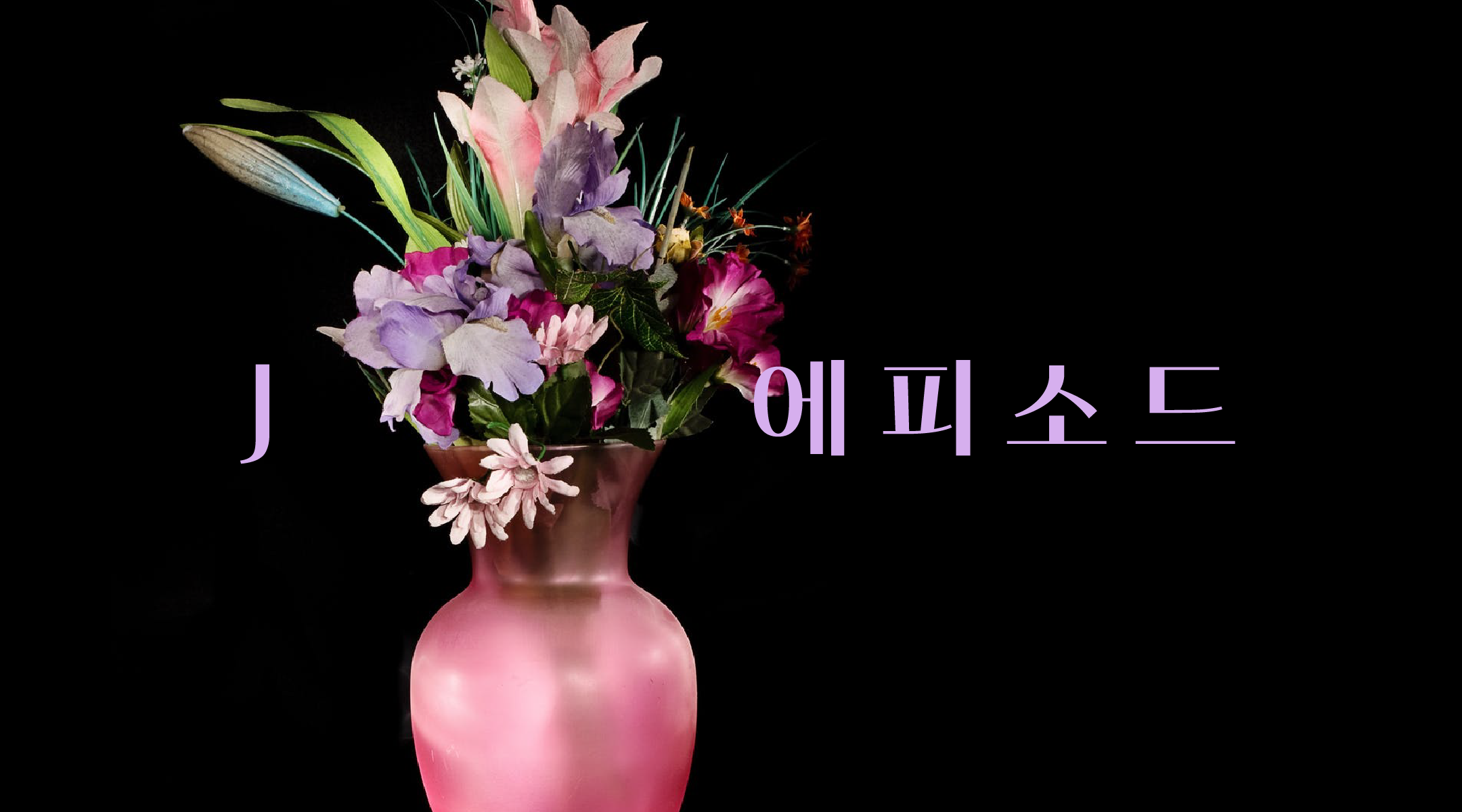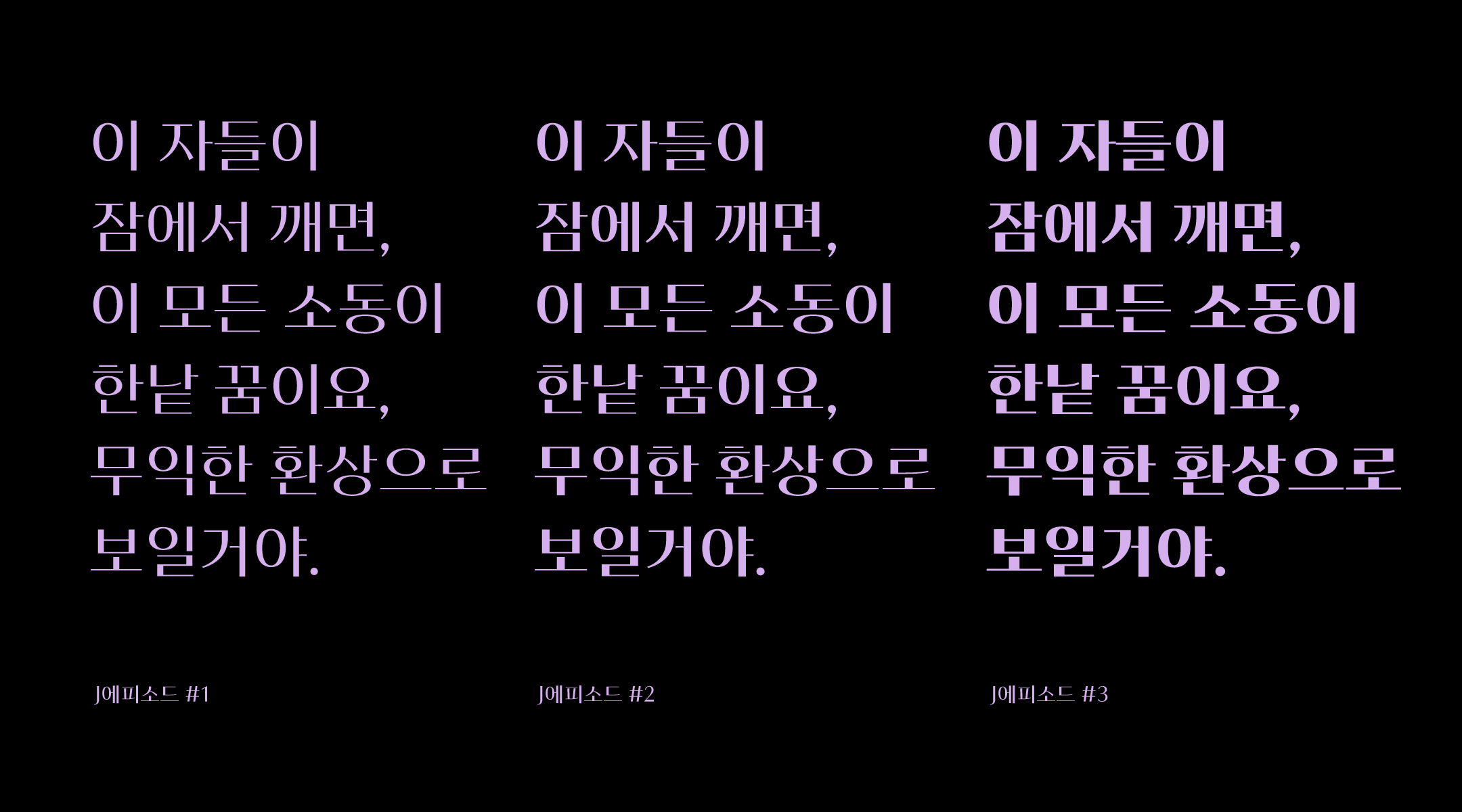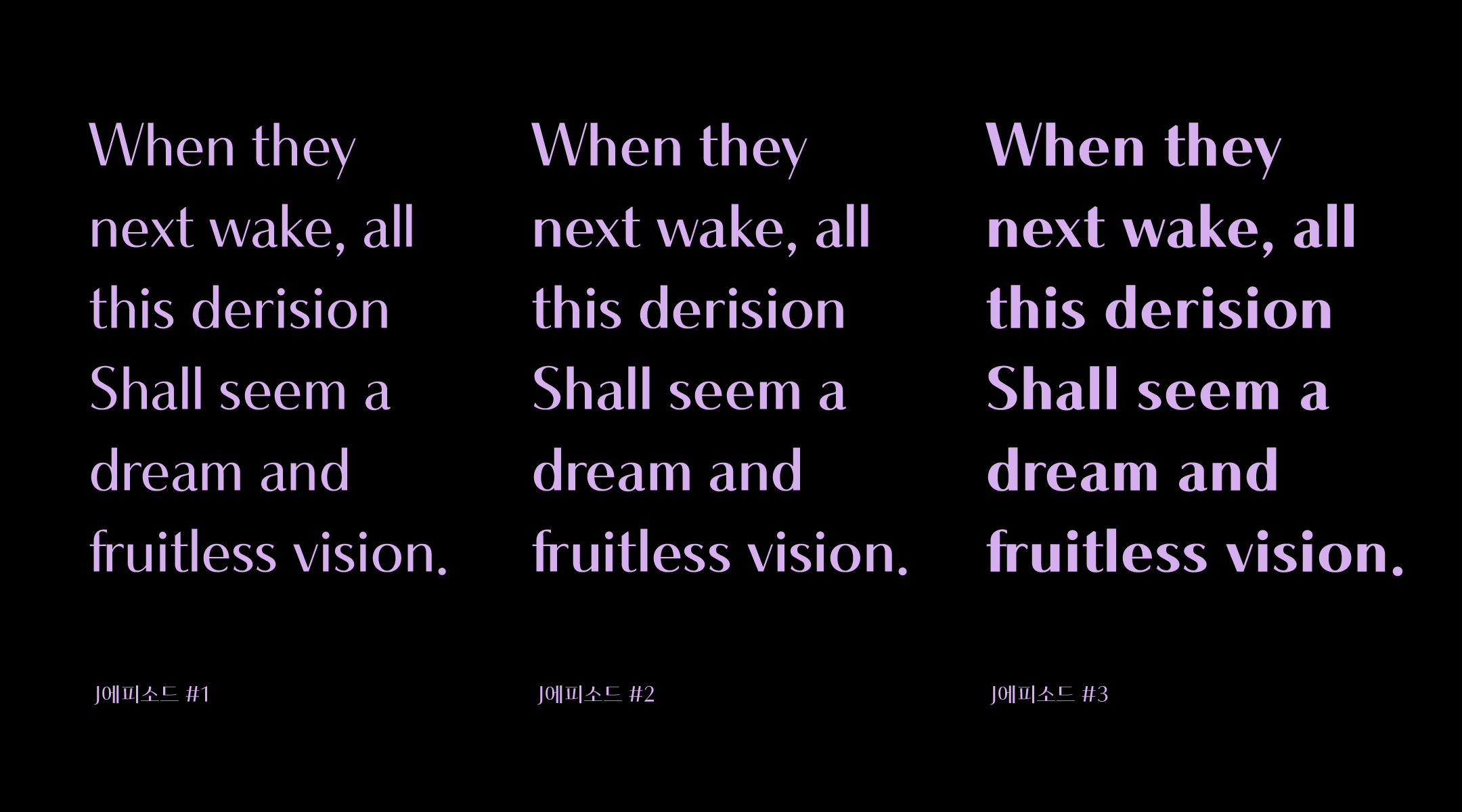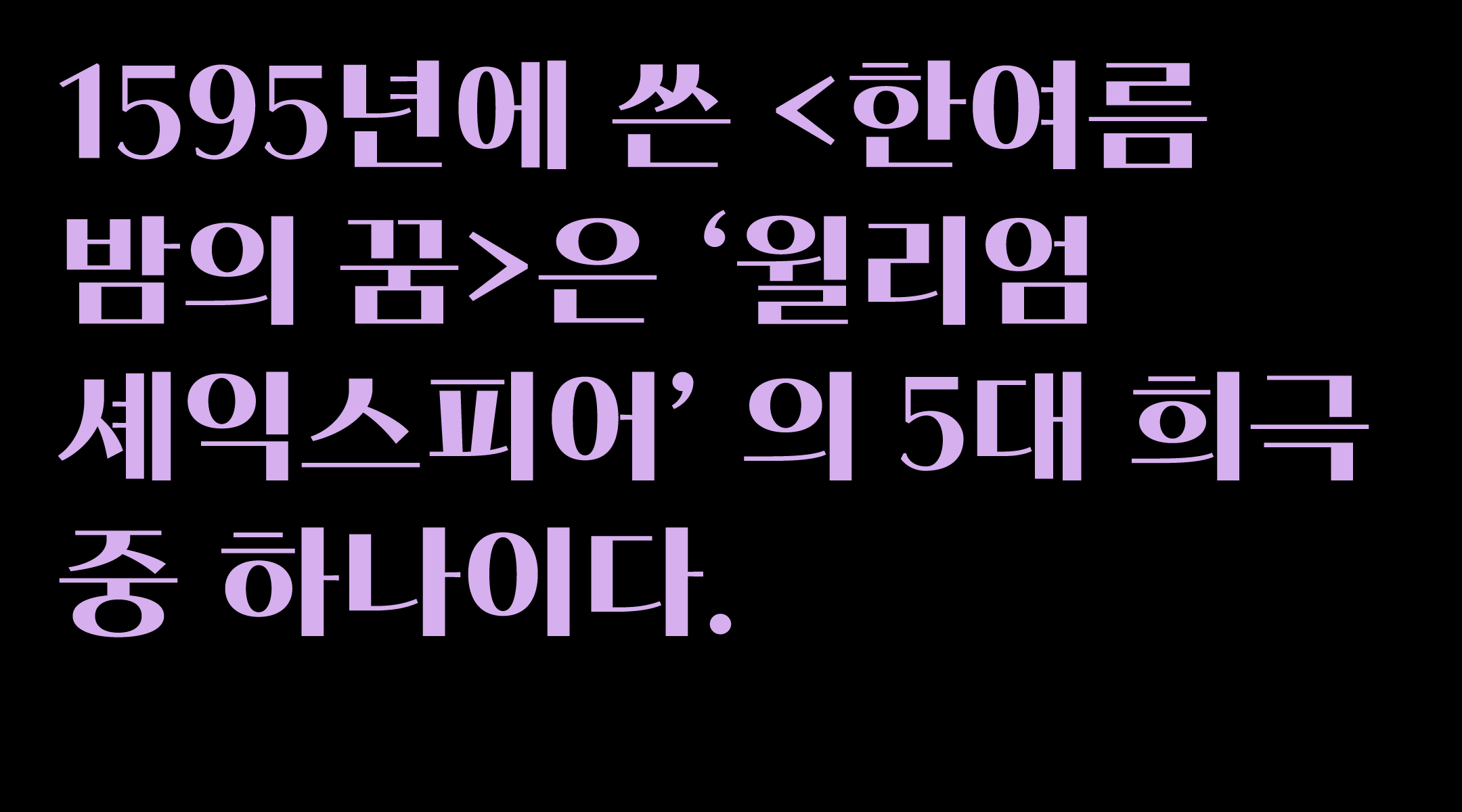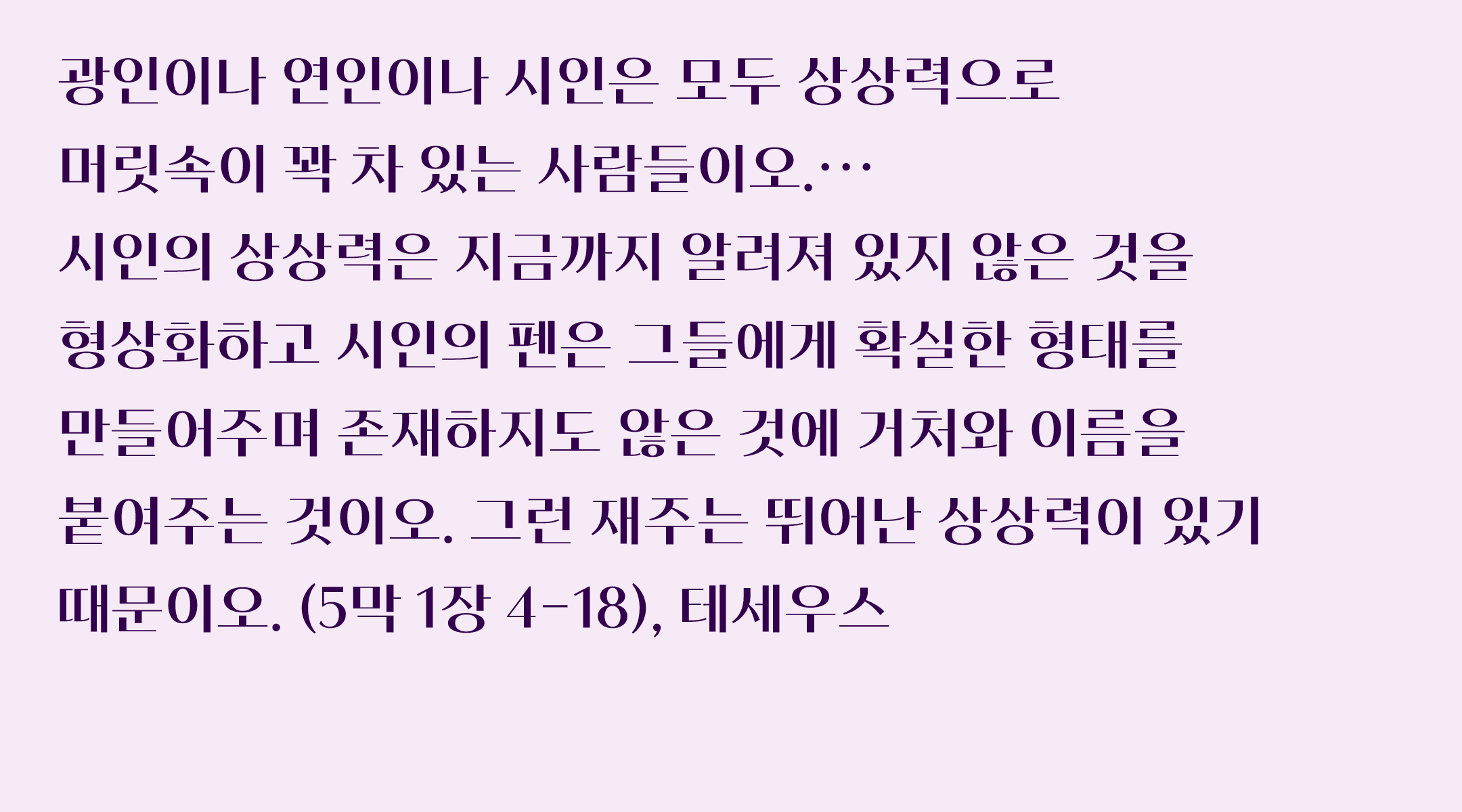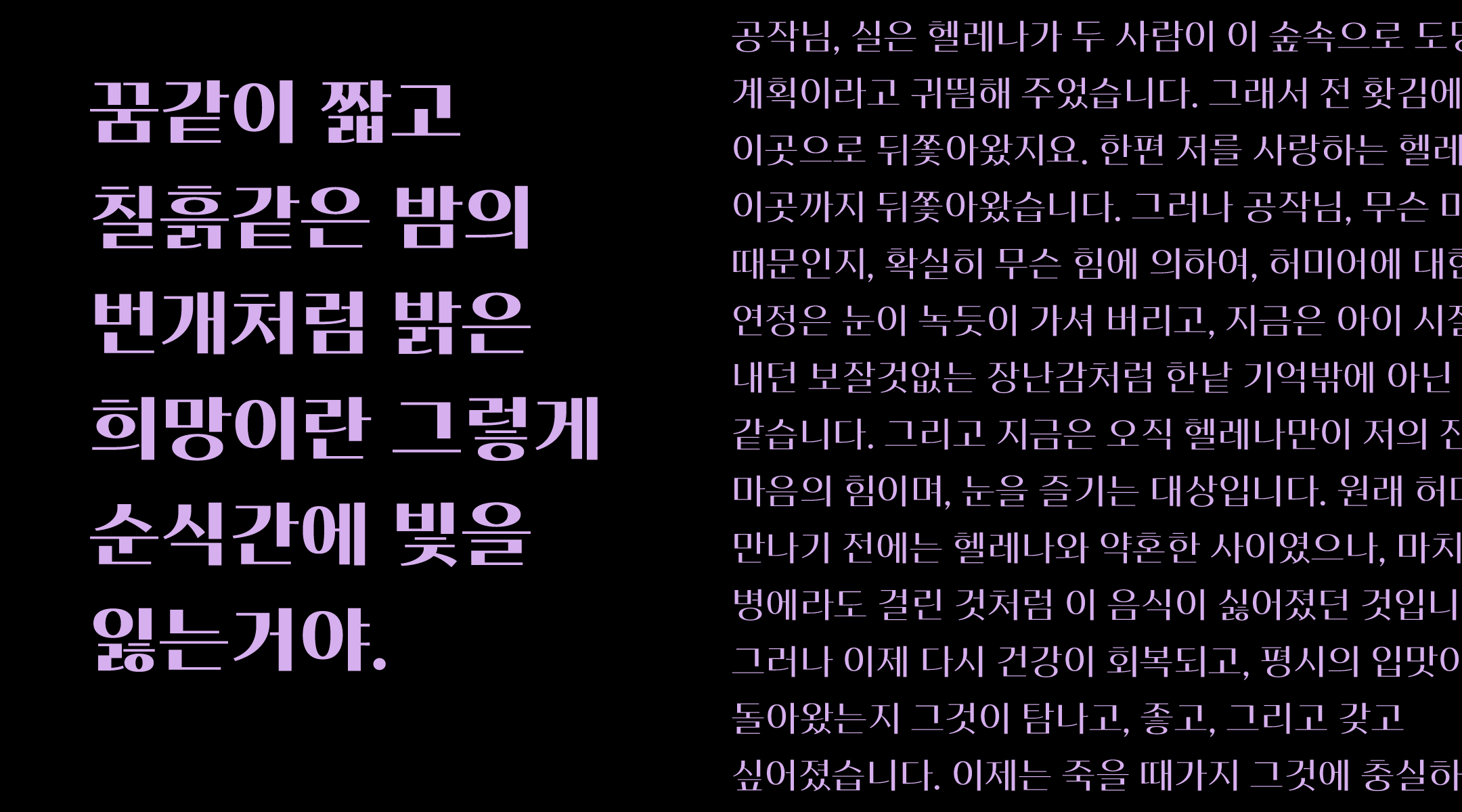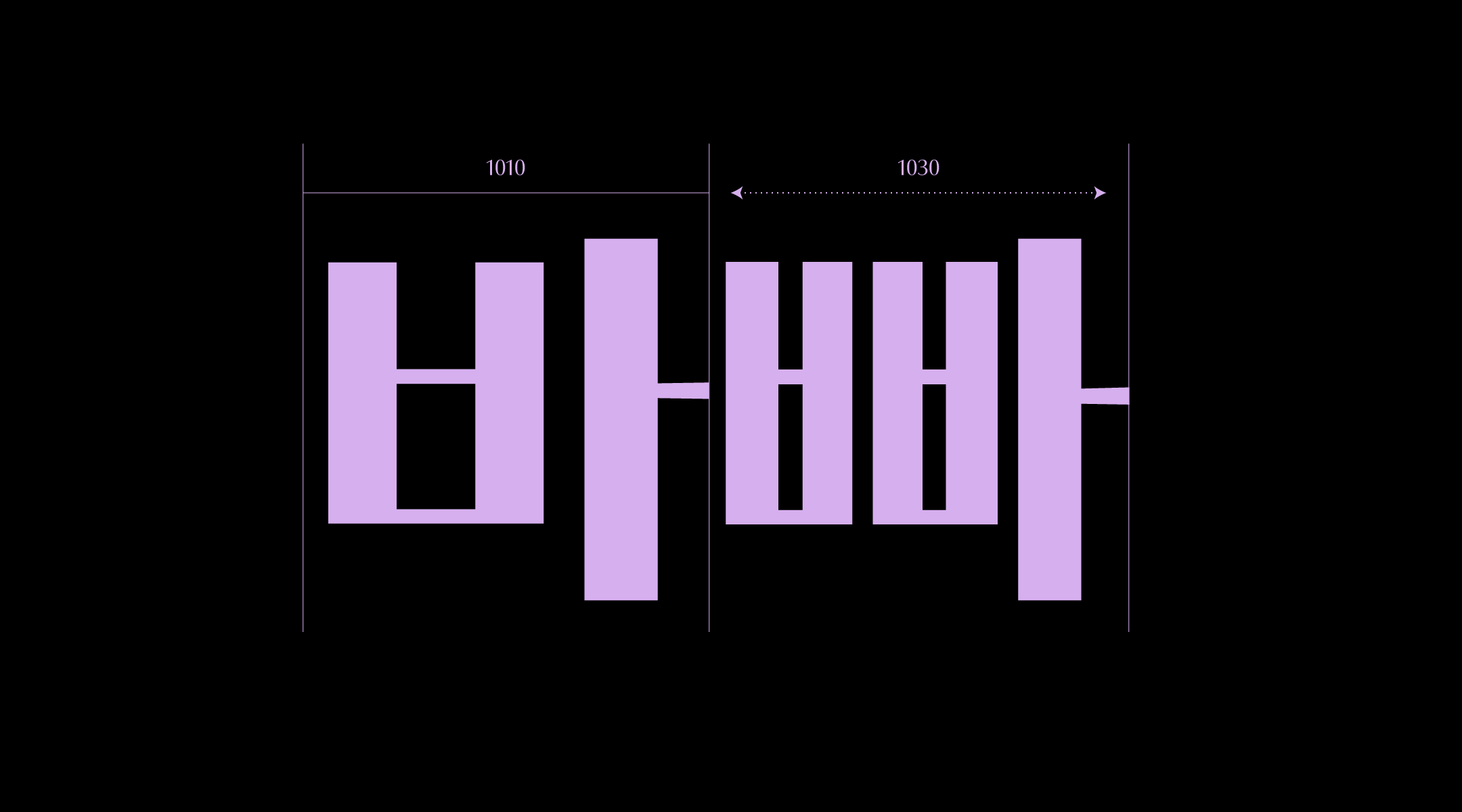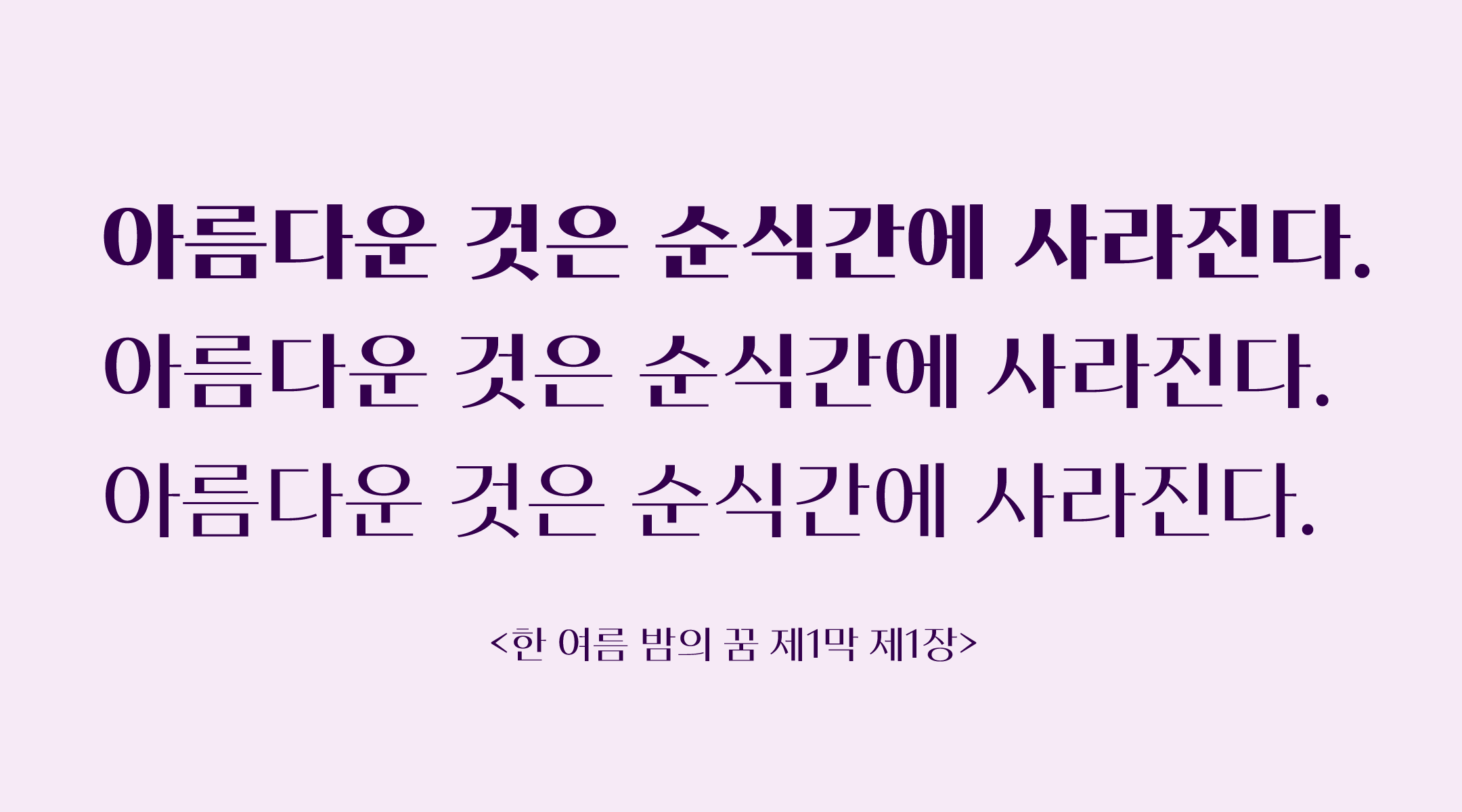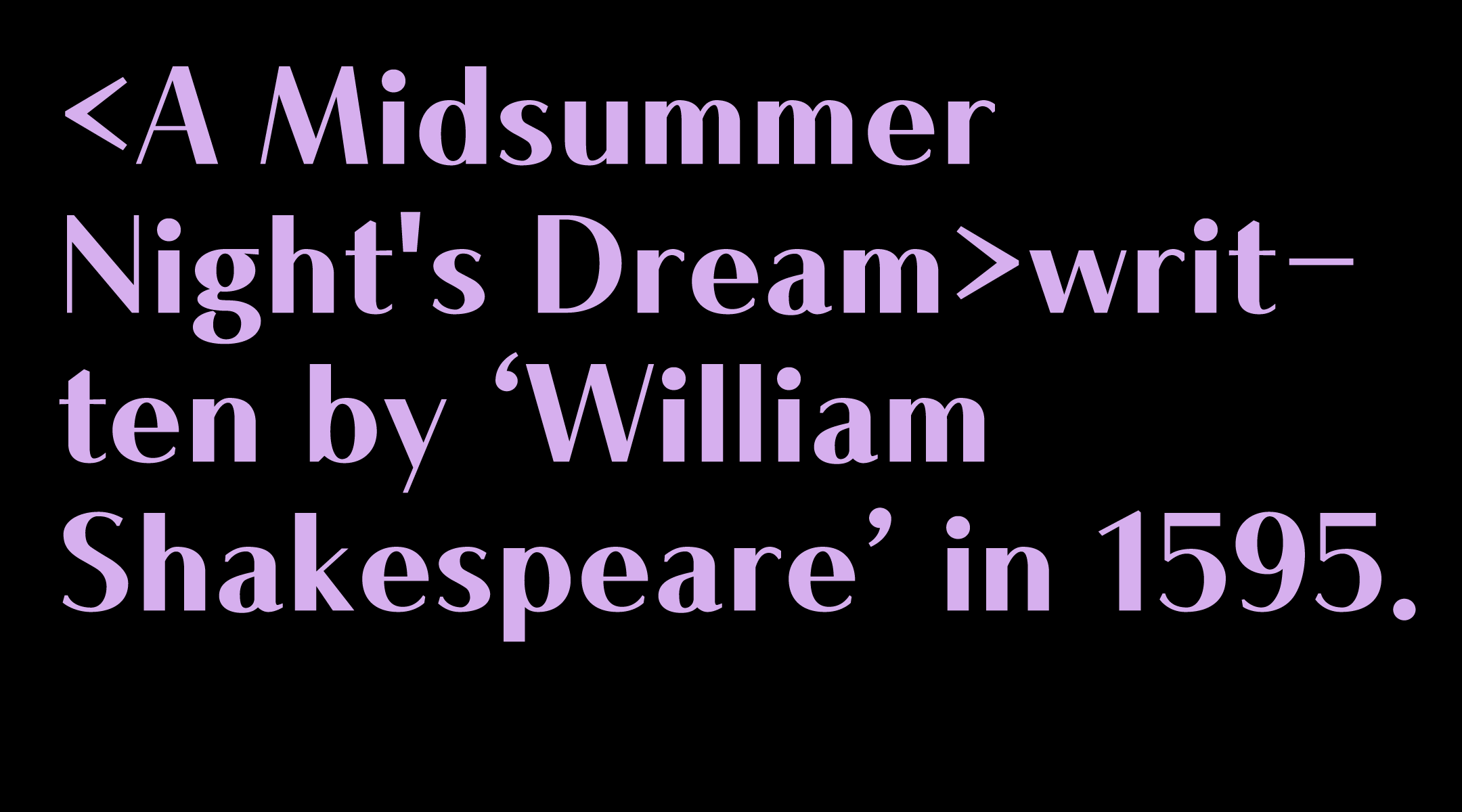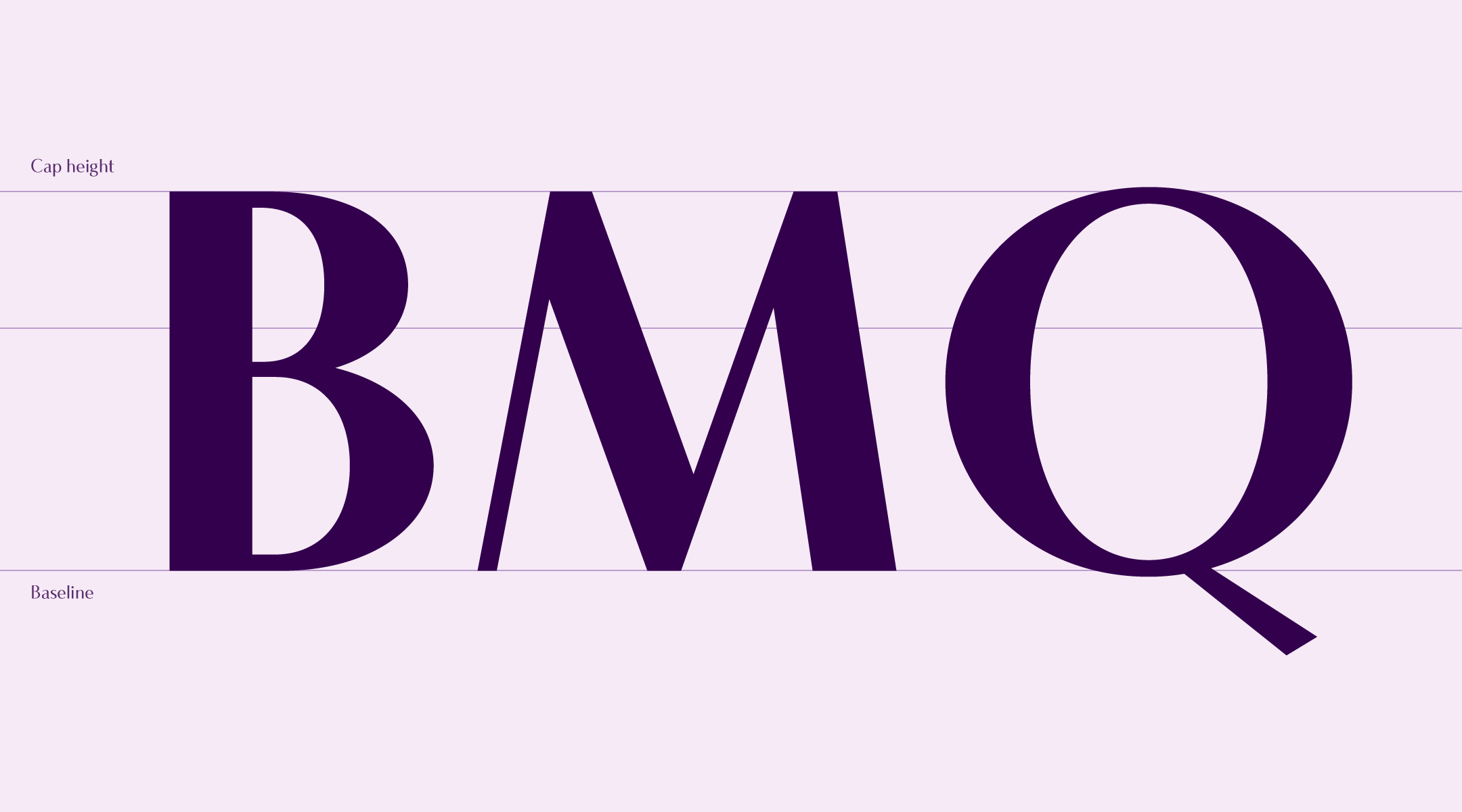
J에피소드
다양한 컨셉으로 활용이 가능하고 독특한 디자인 요소가 많은 서체 시리즈. 개성있는 디테일로 시각적 재미를 더하고 풍부한 이야기를 담을 수 있는 서체이다.
폰트 설명
J에피소드는 일상에서 일어나는 크고 작은 이야기와 함께 하고자 기획된 폰트입니다. 에피소드의 어원은 그리스어로 에페이소도스(epeisodos: 추가해 넣는 것)로 노래와 노래 사이의 대화 부분을 나타내는 것에서 시작되었으나오늘날에는 장편 시리즈 작품의 각’회’를 의미하기도 하고 완결된 '짤막한 이야기’의 뜻으로 많이 사용하고 있습니다. J에피소드 그러한 우리의 이야기에 우아하지만 정제된, 친숙한 목소리를 낼 수 있는 폰트가 되었으면 합니다. 한글 디자인 특징: 에피소드는 그래픽체의 계보를 따르지만 자소의 형태 디자인 및 획을 곡선과 직선의 적절한 분배하여 우아하며 세련된 인상을 줍니다. ‘ㄱ,ㅅ’ 계열 자소에서 보이는 독특한 곡선감은 글자의 풍성하고 우아한 느낌을 강조하며, 가장 큰 분위기를 형성합니다. 초성 ‘ㄴ,ㄷ,ㄹ,ㅌ,ㅍ’의 자소는 일부 글자에서는 '곡선'을 띄지만 받침 글자에서는 '직선'으로 처리해 '깔끔한' 이미지를 보여줍니다.
한글 자폭은 '모임 꼴' 별로 각기 다른 넓이를 가지고 있습니다. '바'에 비교해 획이 많은 '빠'는 더 넓은 자폭을 가져, 글자의 공간 설계를 효율적으로 디자인했습니다. 라틴 디자인 특징 :휴머니스트 산스 양식에서 보여지는 고전적인 느낌과 현대적인 감성이 어우러집니다. 글의 분위기에 어울릴 수 있도록 B,C,D,G등의 글자에서는 곡선미를 살렸고, K,M,N,V등에선 직선의 느낌을 부각시켜 한글처럼 곡선과 직선이 어우러지도록 디자인하였습니다. ‘J/Q’가 이와같은 분위기를 글자에 담아내고 있습니다.